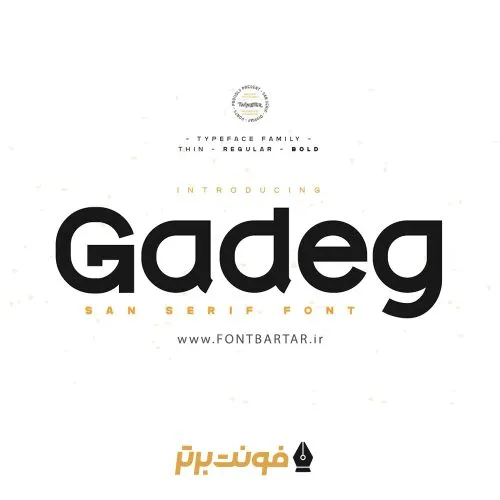
فونت انگلیسی Gadeg
یکی از بهترین فونت هایی که میتوانید در دنیای طراحی از آن استفاده کنید فونت انگلیسی Gadeg است . این فونت لاتین حرفه ای با طراحی فانتزی و رسمی خود از قالب اصلی فونت های انگلیسی ، بسیار زیاد مورد توجه طراحان گرافیک در سراسر جهان بوده و هست .
فونت لاتین gadeg